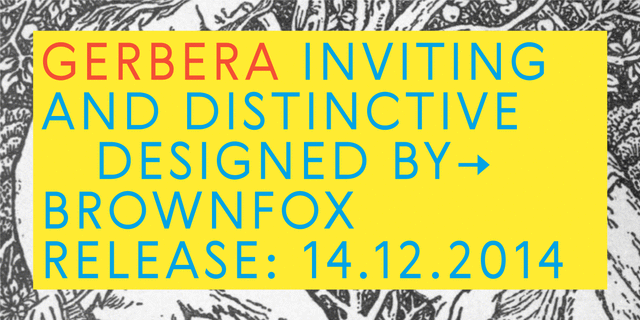
Гербера – это гротеск с отчетливой индивидуальностью, сочетающей геометрические и органические элементы. Шрифт одновременно модный и странный, лаконичный, но своеобразный, сдержанный, но чувственный. Его намеренно измененные классические пропорции прописных знаков и геометрическая структура, уравновешены легким обратным контрастом и защемленными краями изогнутых штрихов. Этот универсальный шрифт поставляется с пятью насыщенностями и поддерживает различные Open Type функции. Гербера включает капитель, альтернативные символы и пунктуацию, пять наборов цифр и поддержку расширенной латиницы и кириллицы. Шрифт разработали Гаянэ Багдасарян и Вячеслав Кириленко в студии Brownfox в 2014 году.
деликатный, чистый, легкий, прохладный, свежий, модный, городской, тонкий, современный, лаконичный, ясный, ровный, понятный, качественный, простой, культурный, интересный, оригинальный, характерный, самобытный, умный, образованный, минималистичный, доступный, элементарный, правильный, прямой, острый, строгий, комфортный, удобный, мотивирующий, ироничный, странный, заметный, броский, яркий
общество, город, парфюмерия, лосьон, красота, туалетная вода, шампунь, косметика, мода, навигация, парикмахерская, диета, дизайн, гигиена, чистота, одежда, коворкинг, интерьер, музей, искусство, инстаграм, обувь, транспорт, аэропорт, метро, лекарство, инновации, архитектура, наука, интернет, мобильная связь, чертеж, инженер, образование Стилистика: